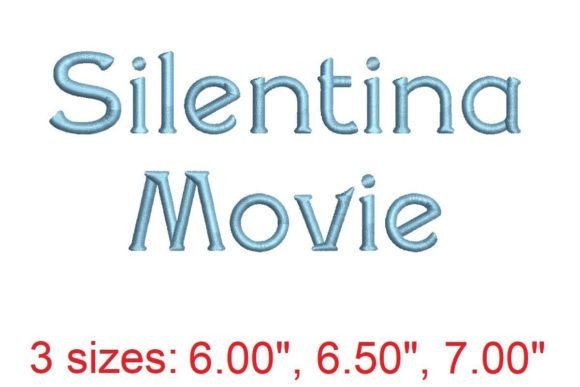
Silentina Movie Embroidery Font
Jika anda sedang mencari aset berkualiti tinggi seperti Silentina Movie Embroidery Font, pakej premium ini merupakan pilihan yang hebat untuk projek kreatif anda.
Sama ada anda mencipta produk POD (Print on Demand), jemputan perkahwinan atau grafik media sosial, Silentina Movie Embroidery Font amat bersesuaian.